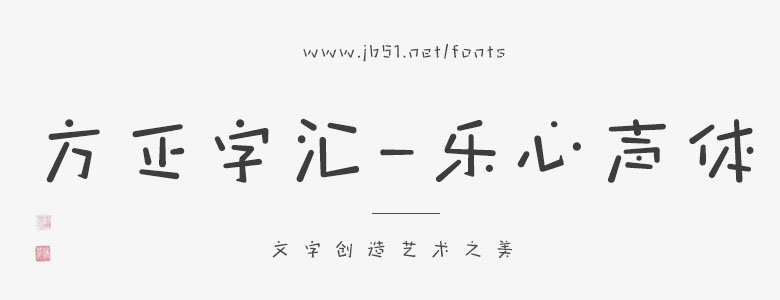
方正字匯-樂心聲體是一款創(chuàng)意卡通字體,在字體中能感受到孩子般的樂趣,調(diào)皮中又不失穩(wěn)重,字形略長,一筆一劃猶如一根根胖乎乎的小手指,粗壯穩(wěn)定且動感十足,看似毫無章法,但組合起來無一絲違和感,筆畫時(shí)細(xì)時(shí)粗,變化明顯,對比強(qiáng)烈,彰顯活潑生動的氣質(zhì),用圓形筆劃演繹來顯示孩子不拘一格的心態(tài),充滿歡樂心聲處處聞的感受,是一款適用于兒童品牌的時(shí)尚字體。